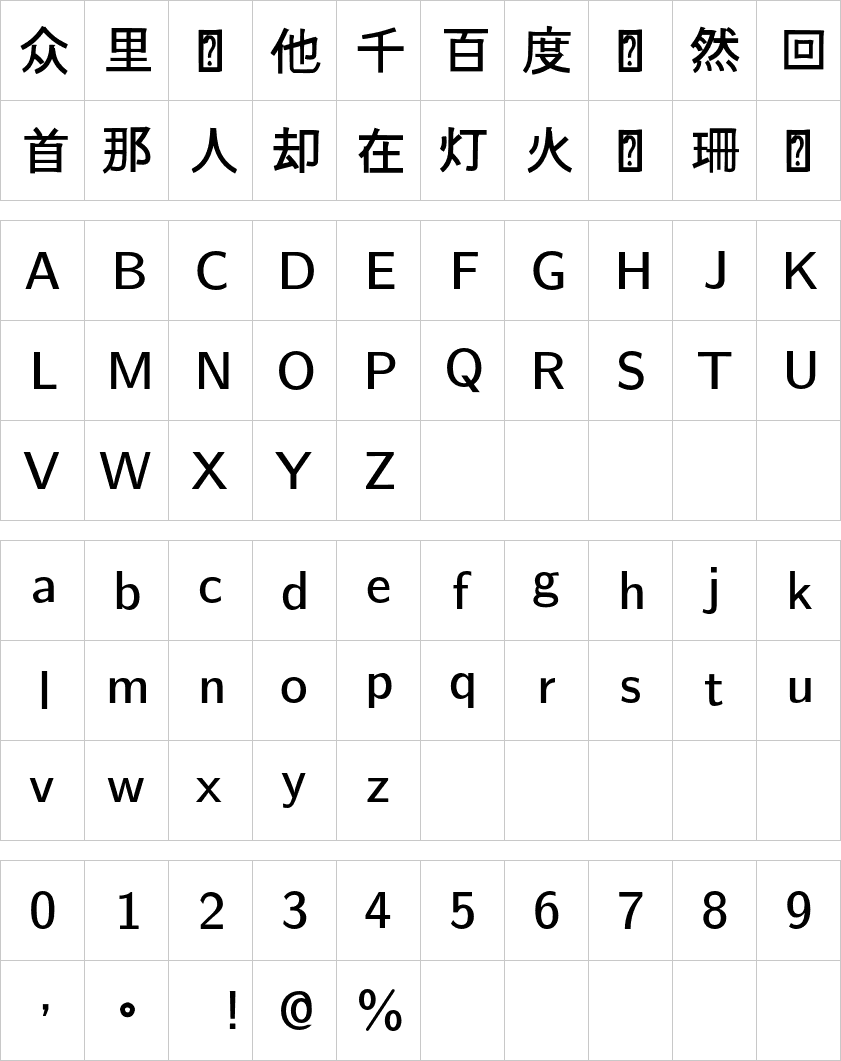
HZ ゴシック
HZ Mincho OpenType字体
这是一个免费/libre OpenType CID键控的日语字体,源自GlyphWiki的CJK数据,具有不同的权重。
拉丁语、希腊语和西里尔字母不是从GlyphWiki派生的,而是从计算机现代Unicode派生的,因为Glyph维基的Kage引擎是为汉字设计的,不擅长LGC。
一些符号来自M+字体和GL Antique字体。